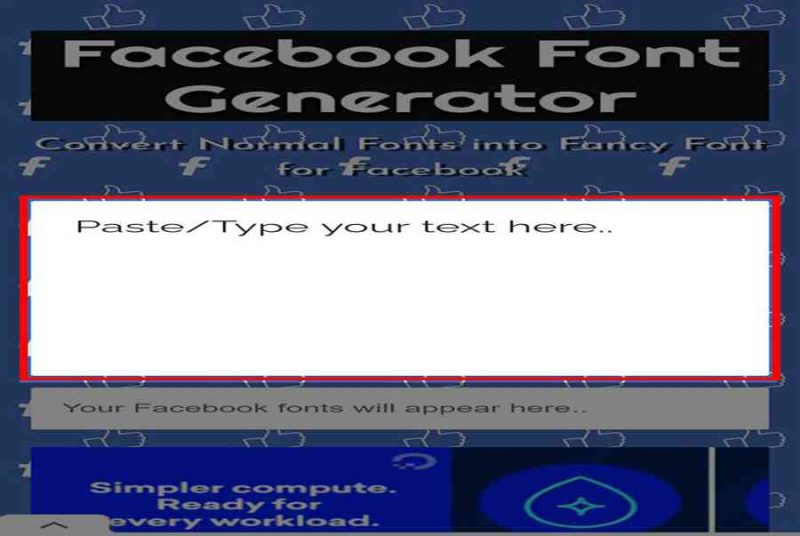
Bạn đã quá nhàm chán với font chữ mặc định của Facebook nhưng không biết cách đổi sang các font khác độc đáo, ấn tượng hơn như thế nào? Hãy cùng theo dõi bài viết này để mình hướng dẫn bạn 5 cách đổi font chữ Facebook độc đáo trên điện thoại, máy tính nhé!
Facebook Font
I. Đổi font chữ Facebook miễn phí trên AhaChat
Giới thiệu về Ahachat:
• Đặc điểm: Là công cụ chuyển đổi font chữ được được phát triển bởi AhaChat, tất cả các font chữ trên công cụ này đều là font Unicode nên có thể hiển thị trên hầu hết mọi nơi có thể dán văn bản như: các trang mạng xã hội, blog, bình luận, diễn đàn,…
• Tính năng: Giúp thay đổi font chữ mặc định bình thường thành các font chữ khác đẹp, độc đáo, mới lạ hơn. Bộ công cụ này hoạt động hầu hết mọi nơi mà Facebook cho phép nhập văn bản: cập nhật trạng thái, tin nhắn, tiểu sử, bình luận,…
Truy cập vào website AhaChat > Nhập văn bản cần chuyển đổi vào ô “Nhập text vào đây” > Lướt tìm font chữ bạn muốn chọn > Chọn biểu tượng Sao chép bên cạnh font bạn muốn đổi > Dán nội dung đã sao chép sang Facebook.
Bước 3: Website sẽ hiển thị văn bản bạn nhập bằng các font chữ khác nhau. Chọn vào biểu tượng Sao chép bên cạnh font chữ bạn muốn chọn.
Bước 4: Dán nội dung vừa sao chép sang bất cứ chỗ nào có thể nhập chữ trên Facebook.
Paste chúng sang Facebook.
Kết quả hiển thị trên Facebook như sau :
FACEBOOKFONT
II. Đổi font chữ Facebook miễn phí trên YayText
Giới thiệu về YayText:
• Đặc điểm: Trang web này bao gồm 25 kiểu chữ đa dạng, in nghiêng, in đậm, gạch chân hay không gạch chân, tất cả đều có.
• Tính năng: Giúp thay đổi font chữ mặc định bình thường thành các font chữ khác đẹp, độc đáo, mới lạ hơn. Bộ công cụ này hoạt động hầu hết mọi nơi mà Facebook cho phép nhập văn bản: cập nhật trạng thái, tin nhắn, tiểu sử, bình luận…
Truy cập vào website YayText > Nhập văn bản cần chuyển đổi vào ô “Your Text” > Lướt tìm font chữ bạn muốn chọn > Chọn Coppy bên cạnh font bạn muốn đổi > Dán nội dung vừa sao chép sang Facebook.
Bước 2: Nhập văn bản cần chuyển đổi vào ô “Your Text“.
Website sẽ hiển thị văn bản bạn nhập bằng các font chữ khác nhau. Chọn Copy bên cạnh font chữ bạn muốn chọn.
Bước 3: Website sẽ hiển thị văn bản bạn nhập bằng các font chữ khác nhau. Chọn Copy bên cạnh font chữ bạn muốn chọn.
Website sẽ hiển thị văn bản bạn nhập bằng các font chữ khác nhau. Chọn Copy bên cạnh font chữ bạn muốn chọn.
Bước 5: Dán nội dung vừa sao chép sang Facebook. Kết quả hiển thị như dưới đây:
Kết quả hiển thị như dưới đây:
Lưu ý :
• Đối với những dòng điện thoại đã cũ, hoặc lâu đời sẽ không nhìn thấy những kiểu chữ đặc biệt này. Thay vào đó là những ô vuông dạng ký tự đặc biệt nhìn không được đẹp mắt.
• Những từ có nhiều ký tự sẽ bị thiếu đi khi hiển thị. Đặc biệt là ký tự tiếng Việt có dấu.
Một số font bị lỗi hiển thị như dưới ảnh :
Một số font bị lỗi hiển thị:
III. Đổi font chữ Facebook trên Symbols & Emoticons
Giới thiệu sơ qua về Symbols & Emoticons:
• Đặc điểm: Là công cụ chuyển đổi font chữ được được phát triển bởi Symbols & Emoticons. Với độ đa dạng gồm 20 kiểu font chữ độc đáo, mới lạ, tha hồ cho bạn lựa chọn.
• Tính năng: Giúp thay đổi font chữ mặc định bình thường thành các font chữ khác đẹp, độc đáo, mới lạ hơn. Bộ công cụ này hoạt động hầu hết mọi nơi mà Facebook cho phép nhập văn bản: cập nhật trạng thái, tin nhắn, tiểu sử, bình luận…
1. Hướng dẫn nhanh
Truy cập vào website Symbols & Emoticons > Tại khung “Your text here…” bạn nhập trạng thái, comments mà bạn muốn chuyển đổi font chữ > Nhấn vào Convert > Lướt xem danh sách kiểu chữ hiển thị bên dưới > Chọn Copy font mà bạn muốn đổi > Dán vào nơi bạn muốn nhập văn bản trên Facebook.
2. Hướng dẫn chi tiết
Bước 1: Truy cập vào website Symbols & Emoticons.
website Symbols & Emoticons
Bước 2: Tại khung “Your text here…” bạn nhập trạng thái, comments mà bạn muốn chuyển đổi font chữ.
website Symbols & Emoticons
Bước 3: Nhấn vào Convert.
website Symbols & Emoticons
Hệ thống sẽ hiện ra đoạn văn mà bạn vừa nhập dưới dạng nhiều font như sau:
Hệ thống sẽ hiện ra "đoạn văn" mà bạn vừa nhập dưới dạng nhiều font như sau:
Bước 4: Lướt xem danh sách kiểu chữ hiển thị bên dưới. Chọn Copy font mà bạn muốn đổi.
Hệ thống sẽ hiện ra "đoạn văn" mà bạn vừa nhập dưới dạng nhiều font như sau:
Bước 5: Dán vào nơi bạn muốn nhập văn bản trên Facebook. Kết quả hiển thị như hình bên dưới:
Lướt xem danh sách kiểu chữ hiển thị bên dưới.
Lưu ý:
• Các Font ở đây đều không phải là Font Unicode nên thường gặp phải lỗi hiển thị.